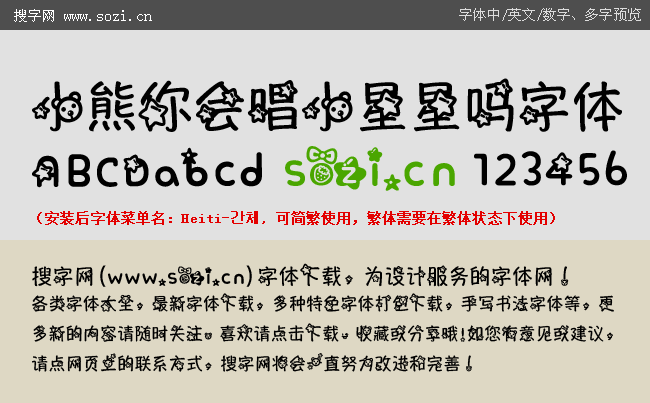
小熊你會(huì)唱小星星嗎字體
搜字網(wǎng)給大家提供一款很卡通的手機(jī)中文字體下載。修改者將它命名為小熊你會(huì)唱小星星嗎字體,這款手機(jī)字體是仿照兒童手寫風(fēng)格的卡通手寫字體,結(jié)構(gòu)帶有POP字體風(fēng)格,字體筆畫間還穿插了非常有趣的卡通圖案,特別適合喜歡手機(jī)字體個(gè)性一些的朋友在手機(jī)上安裝使用。